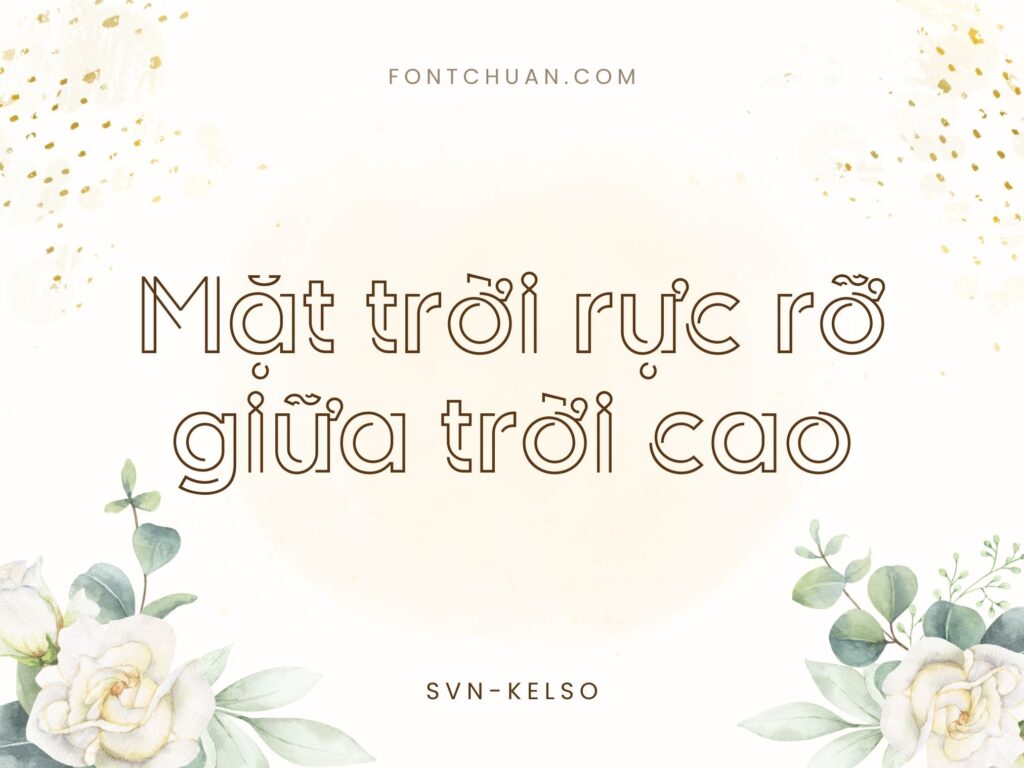
Font SVN Kelso là phiên bản Việt hóa của kiểu chữ Kelso, được thực hiện bởi STYLEno.1 Fonts. Kelso là một font hiển thị độc đáo, trong đó mỗi ký tự được thiết kế bằng một đường nét liên tục, tạo nên sự liền mạch và nhịp điệu trong thiết kế. Phong cách outline của font này mang lại vẻ hiện đại và thu hút, phù hợp cho các dự án yêu cầu sự nổi bật và sáng tạo.
SVN Kelso lý tưởng cho các thiết kế như logo thương hiệu, tiêu đề, bao bì sản phẩm và các ấn phẩm truyền thông. Các ngành nghề như quảng cáo, giáo dục và công nghệ có thể tận dụng font này để tạo điểm nhấn trong thiết kế. Ngoài ra, font cũng thích hợp cho các sự kiện như Tết, Giáng sinh, Valentine và các lễ hội khác.